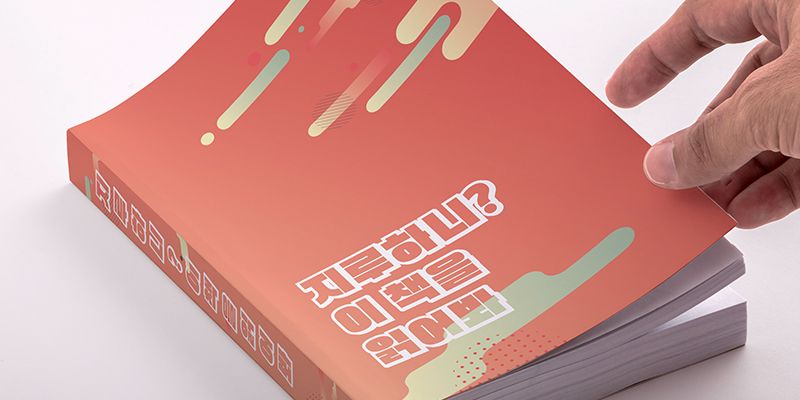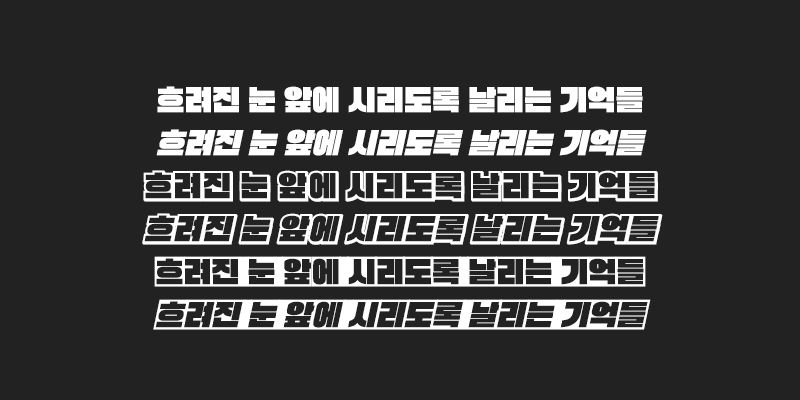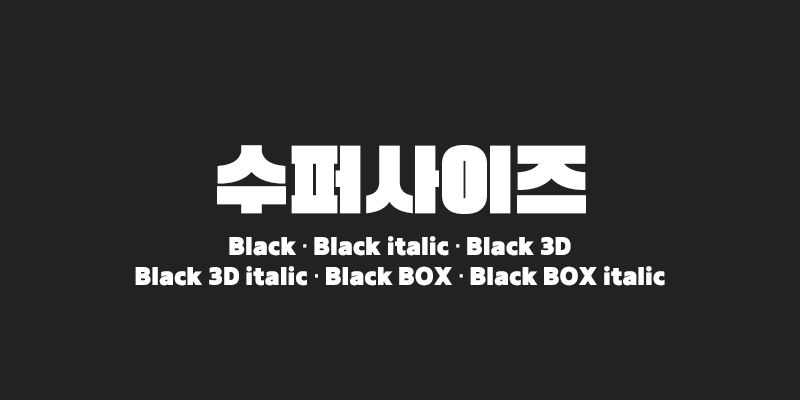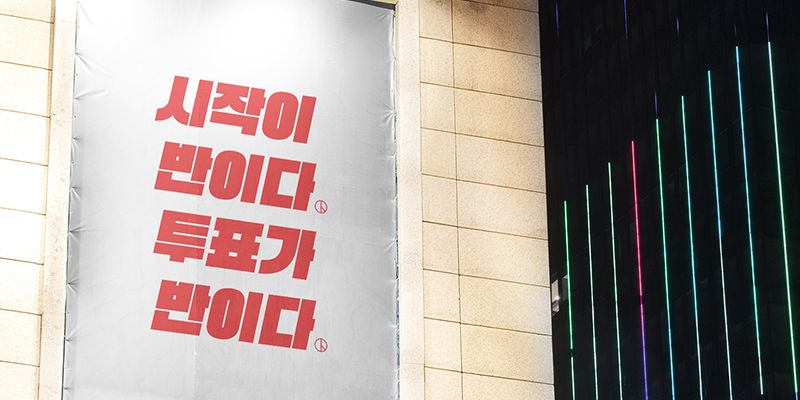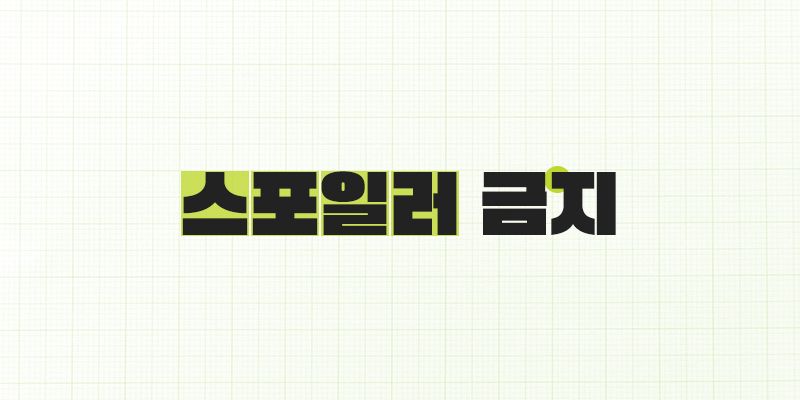
210 Supersize ist eine auffällige und kraftvolle Schrift, die in einer Auswahl verschiedener Spezialeffekt-Varianten erhältlich ist. Sie ist in einer extrafetten Variante erhältlich, die sich ideal für alle Situationen eignet, in denen die Aufmerksamkeit des Betrachters geweckt werden soll. Die kursiven Versionen sorgen für ein Gefühl von Geschwindigkeit und die 3D-Versionen verleihen Ihrem Design noch mehr Wirkung.